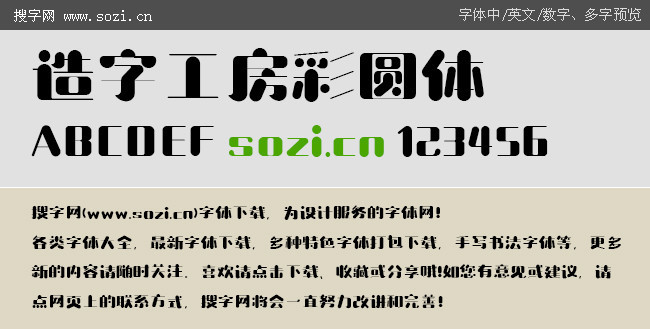
造字工房彩圓體
搜字網(wǎng)給大家提供一款造字工房彩圓體中文字體下載,造字工房彩圓體該字體線(xiàn)條粗壯有力,字形圓潤(rùn),整體筆畫(huà)設(shè)計(jì)自然美觀(guān),字形簡(jiǎn)約,曲線(xiàn)優(yōu)美。適用于海報(bào)設(shè)計(jì)、包裝設(shè)計(jì)、書(shū)籍封面設(shè)計(jì)等應(yīng)用。(本字體為個(gè)人非商用版,如需要商用請(qǐng)聯(lián)系官方購(gòu)買(mǎi)版權(quán))